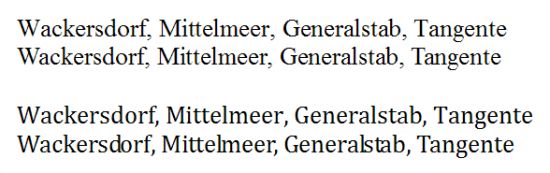
Kerning der Cambria in MS Office??
Hi Freunde des guten Satzes, ich bin
* großer Fan der neuen MS-Systemschriften
* bemüht um ansehnliche Schriftstücke
* beruflich notgedrungen Dauernutzer von MS-Office
... und in dieser Kombination seit heut Nachmittag confused: MS will die Cambria offenbar als Nachfolger der TNR positionieren, wenn ich manche Beobachtung im neuen Office richtig deute. AAAAber: Schalt ich in Word das Kerning ein, produziert genau diese Schrift einen völlig desolaten Satz, ich häng mal ein pdf an(ist am Screen und im Druck identisch). Bisher hatte ich nur so eine vagabundierende Version der Cambria unter Office 2003 in Gebrauch und hab das als beta-Fehler abgetan. Aber nu?
Könnt ihr das reproduzieren, kann das sein?
das kann man dort ein und ausschalten?
...seit bestimmt Version 4.0 unter Win 3.1 oder so :D in der Dialogbox zur Zeichenformatierung, Register "Zeichenabstand", Checkbox zu "Unterschneidung ab ...".
... jetzt wisst ihr ja, wo ihr mal prüfen könnt :)
aaah, da sieht man mal wieder das ich word nur zum copy & paste
von gelieferten vorlagen nutze ;)
bei meiner cambrina ändert sich gar nix.
die scheint also gar kein kerning zu besitzen.
Robert: Zum einen musst du bei "Unterschneidung ab ... pt" einen Wert eingeben, der klein genug ist, dass das Kerning auch für Größen um 10pt greifen (ich gebe immer 1pt an, das ist das kleinstmögliche). Sonst greift das Kerning nur bei großen Schriftgrößen, und lässt es unterhalb der Grenze außen vor.
Zum anderen bin ich mir nicht mehr sicher, ob Word (vor 2007) Opentype-Kerning beherrscht. Ich meine da mal was gelesen zu haben, kann aber sein dass ich Sachen durcheinanderbringe.
Nun ein Test mit Openoffice 2.1 (da heißt das "paarweises Kerning" und es gibt keine Mindestgröße):
Times und Arial kernen heftig zwischen V und o (Testwort "Vogelgrippe")
Die neuen (Cambria, Candara) zwischen V und o offenbar gar nicht, dafür ändern sich die Abstände zwischen r und i bei Cambria minimal, bei Candara hingegen zwischen l und g. Da scheint also was interpretiert zu werden.
Ob das jetzt auf Word umlegbar ist? Bitte ausprobieren, ich hab es nicht mehr.
Wie gesagt, zwischen r und i sollte bei Cambria eine leichte Veränderung sichtbar werden (Schriftgröße etwa 100, um was zu sehen).
Robert: Zum einen musst du bei "Unterschneidung ab ... pt" einen Wert eingeben, der klein genug ist, dass das Kerning auch für Größen um 10pt greifen (ich gebe immer 1pt an, das ist das kleinstmögliche). Sonst greift das Kerning nur bei großen Schriftgrößen, und lässt es unterhalb der Grenze außen vor.
is schon klar, allerdings hat sich bei arial und co auch was geändert, bei
den neuen ms fonts aber nix.
Nachtrag:
Die Sache scheint doch diffizil zu sein. Die Cambria beinhaltet als einzige der neuen Systemfonts auch eine Unzahl mathematischer Sonderzeichen und liegt (wohl deshalb?) in einem anderen Format vor als Corbel, Calibri und co. Das monierte miserable Kerning tritt unter Word 2003 genauso auf wie unter Word2007 im Kompatibilitätsmodus. Darin kann man "alte" Dokumente öffnen, wenn man sie hinterher wieder so abspeichern will, dass sie auch unter älteren Word-Versionen lesbar bleiben. Konvertier ich die "alten" Dokumente oder erstell neue, so ist das Kerning auch mit der Cambria ausgezeichnet (und auch wirksam - Vo z.B.). Word scheint also nur im neuen Dateiformat das "neue" OpenType-Kerning zu unterstützen, das verschiedentlich angesprochen wurde.
btw: man möge mir bitte Einwände nennen, was in der jetzt vorliegenden Form außerhalb der Druckvorstufe (z.B. rgb/cmyk-Problem, völlig klar) an Word verwerflich ist.
man möge mir bitte Einwände nennen, was in der jetzt vorliegenden Form außerhalb der Druckvorstufe (z.B. rgb/cmyk-Problem, völlig klar) an Word verwerflich ist.
›Verwerflich‹ ist an Word natürlich nichts; es ist ein tolles Programm, das vielen Millionen Nutzern gute Dienste leistet.
Die Abneigung richtet sich vielleicht eher gegen das Word-eigene .doc-Format: Es ist proprietär, d.h. um es (100%) zuverlässig und veränderungsfrei zu öffnen, benötigt man selbst eine Word-Version. Und zwar möglichst die gleiche. Schon bei der Mac-Variante, die sich ja gerade bei vielen Grafikern großer Verbreitung erfreut, blühen manchmal unschöne Überraschungen: Fußnoten weg, Zeichenkodierung verändert, von Formatierungen ganz zu schweigen …
Da mag sich mancher denken: Wieso muss ich mir zusätzlich ein Microsoft-Produkt kaufen – welches ich selbst gar nicht zum Arbeiten brauche –, nur, um die angelieferten Textdaten anderer öffnen zu können?
Weil viele ›Normalos‹ oft nichts anderes als Word kennen (und so auch nichts von derlei Problemen ahnen), missbrauchen sie das .doc-Format zum Weiterreichen/Austausch von Daten – und dafür ist es einfach nicht gedacht. Bessere Alternativen sind .rtf oder, je nach Gegebenheit, .pdf.
Ich habs ausprobiert mit Word 2003 (Win) – oben TNR, unten Cambria.
Erste Zeile jeweils ohne Unterschneidung, zweite Zeile jeweils mit.